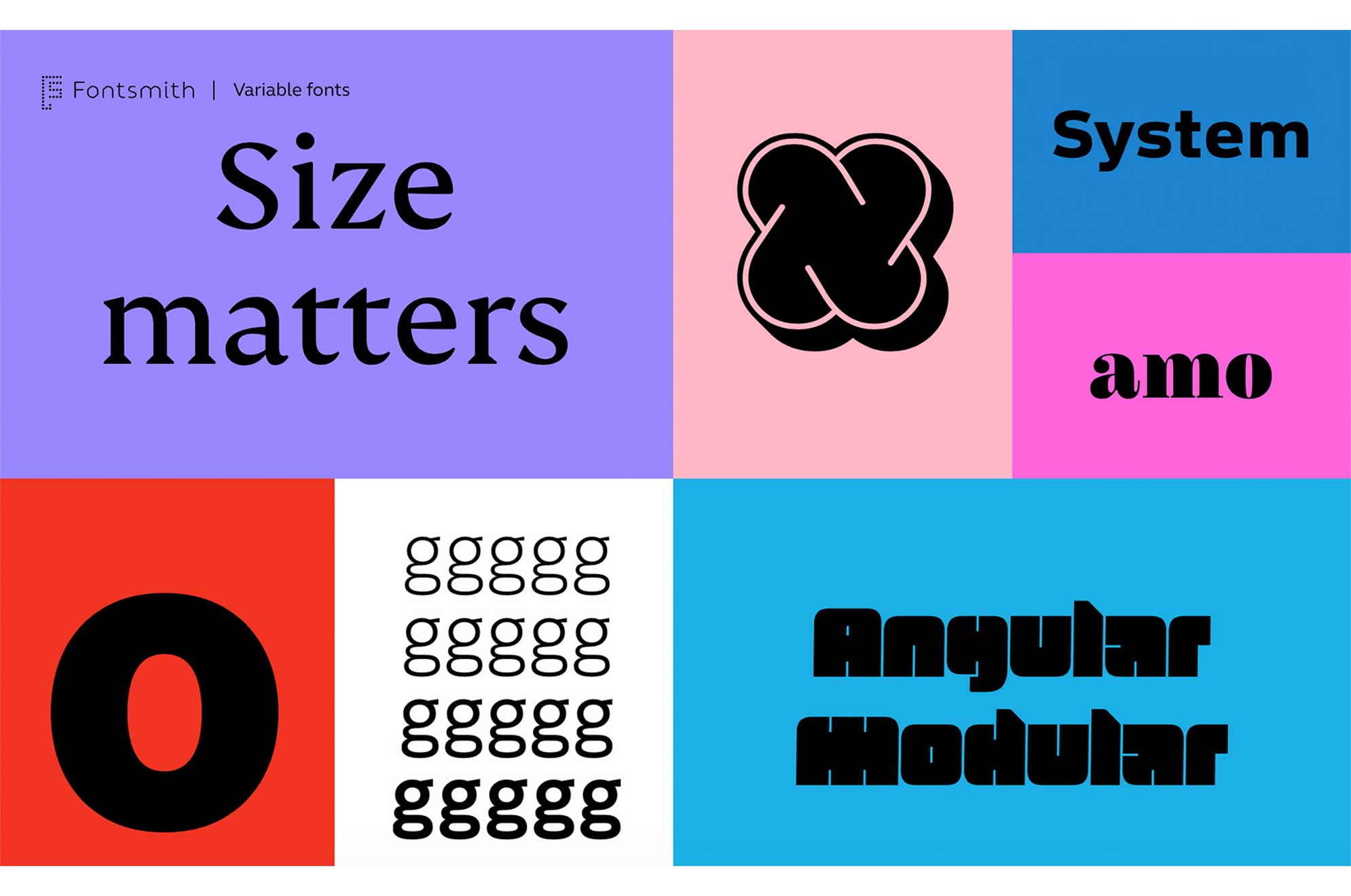
Obwohl die Technologie der variablen Fonts bereits vor rund drei Jahren im Markt eingeführt wurde, ist sie einer nicht ganz kleinen Anzahl Kreativer noch nicht vertraut: In der kürzlich erneut durchgeführten und inzwischen recht bekannten Umfrage von Mary Catherine Pflug zu den Kaufgewohnheiten von Schriften (“Font Purchasing Habits Survey“) gab ein Drittel der dort befragten Designer an, dass ihnen die Vorteile der variablen Schriften nicht bekannt seien. Und 39 Prozent hatten keine Ahnung, was variable Schriften überhaupt sind. Eine ziemlich ernüchternde Statistik für uns Schriftgestalter, denn wir sind alle überzeugt und begeistert von den Möglichkeiten, die diese Technologie uns eröffnet.
Mit variablen Fonts ist (fast) alles möglich
Einer der Kernaspekte variabler Schriften ist ihre enorme Leistungsfähigkeit und die damit einhergehende Tatsache, dass Marken mit ihnen völlig neue Möglichkeiten für ihre visuelle Kommunikation erhalten. Und weil wir Designer glauben, dass Schrift der Eckpfeiler jedes Corporate Designs ist, betrachten wir das als eine sehr gute Nachricht. Denn die Technologie verleiht der Schrift mehr Kraft und Energie, um die Identität einer Marke zu vermitteln.
Ich bin überzeugt, dass mit variablen Schriften eine neue Ära im Schriftdesign beginnt, denn mit ihnen ist (fast) alles möglich. Etwa weil eine variable Schrift eine einzelne, optimierte Schriftdatei ist, die sich aber wie eine komplette Schriftfamilie verhält und damit eine breite Palette von Stilen bereitstellen kann. Wenn eine traditionelle Schriftfamilie beispielsweise die Strichstärken Thin, Light, Regular, Bold und Black anbietet, kann diese als variable Schrift nicht nur alle diese Gewichtungen in einer Datei enthalten, sondern auch zig Zwischen-Strichstärken – und das in feinen Abstufungen. Dabei bleibt die Dateigröße überraschend klein, denn eine Variable Font-Datei enthält nicht die Beschreibung aller Stilzustände, sondern lediglich die Regeln, wie ein gewünschter Zustand entstehen soll.
Einen spielerischen Einstig in die Variable-Font-Technologie bietet diese Demo-Site von FontSmith, eine Foundry, die Monotype Anfang 2020 übernommen hat. Dort lassen sich mehrere Schriftfamilien per Schieberegler und mit eigenen Texten ausprobieren.
Die Stärke der variablen Font-Technik zeigt sich vor allem bei Großfamilien, wie beispielsweise der Universität Next, die 7 Strichstärken (Hairline bis Black), 3 Breiten (Condensed, Normal, Extended) und die dazugehörigen Kursiven bietet, also aus 7×3+21 = 42 Fonts besteht
…alle 42 Schnitte der klassischen Univers Next sind nun in einer einzigen Datei untergebracht, die nur 948 KB groß ist. Doch damit nicht genug, denn …
… tatsächlich liefert die Variable Font-Datei fast 80.000 Varianten der Univers Next aus, denn die Strichstärken-Achse verfügt über 600 statt „nur“ 7 Stufen, die Breite bietet 65 Abstufungen (statt 3) und die Kursiven sind natürlich auch enthalten. Fazit: variable Fonts sind kompakt, leicht zu handhaben und können über 1000 mal mehr Schnitte enthalten, was die typografische Freiheit enorm beflügelt.
Variable Fonts bieten Marken ein flexibles typografisches Werkzeug
Die Erfahrung zeigt, dass Unternehmen und bekannte Marken neuen Technologien gegenüber sehr aufgeschlossen sind. Die Technologie der variablen Schriften gibt Marken ein flexibles typografisches Werkzeug für eine breite Palette von Medien an die Hand. Für einen TV-Sender oder Streaming-Dienst hieße das etwa, dass Untertitel automatisch auf die Hintergrundfarbe reagieren und sich Strichstärken entsprechend ändern, so dass die visuelle Konsistenz und Lesequalität hoch bleibt – egal was im Hintergrund passiert. Variable Schriftarten können so programmiert werden, dass die Typografie dynamisch gestaltet ist. Das verleiht ihnen eine völlig neue, aber nützliche Qualität im digitalen Textdesign, die bei (statischen) Drucksachen wenig Sinn gemacht hätte. Die Möglichkeiten sind unerschöpflich, denn variable Schriften sind adressierbar, d.h. sie können in Echtzeit während ihrer Verwendung kontrolliert werden. Sie reagieren etwa auf Live-Daten (z.B. Heatmaps), auf die Kamera- oder Leseentfernung, auf die Geschwindigkeit eines Fahrzeugs oder auf Gesten. Die Bandbreite reicht von der reinen Kompensation, die dem Leser eine konstante Lesbarkeit garantiert, bis hin zu eher exzentrischen Typografien, bei denen die Buchstaben deutlich auf Lautstärke, Intonation, Bässe, Höhen oder Beats reagieren.
Variable Fonts bieten Entwicklern und Designern dynamische Möglichkeiten
Gegenwärtig erleben wir die Geburt intelligenter, adaptiver Branding-Systeme, bei denen die Schrift an erster Stelle steht und damit praktisch die Hauptrolle spielt. Jetzt ist also der genau richtige Zeitpunkt, sich mit variablen Schriften zu befassen und Antworten auf ein paar wichtige Fragen zu entwickeln: Wie schnell schneiden variable Schriften auf Webseiten ab? Wie weit können die Achsen einer variablen Schriftgestaltung gehen, bis sich das Erscheinungsbild von der visuellen Identität der Marke abhebt? Steigern variable Schriften die Markentreue oder gefährden sie die Corporate Identity? Sollten sehr bekannte Marken ein Schriftenexperiment wagen, oder besser nicht?
Entwickler und Designer zögern noch immer, variable Fonts anzuwenden. Aber langsam macht sich ein Wandel bemerkbar: Immer neue Ideen für Projekte entstehen, die dynamisch denken und sich von den Beschränkungen statischer Schriften lösen wollen. Die Nachfrage nach reaktionsschnellen, anpassungsfähigen Schriften wächst und konkrete Fragen zu variablen Fonts erreichen die Kreativszene. Das ist eine gute Nachricht, denn mit dem Einsatz variabler Schriften erleben visuelle Markenerlebnisse eine neue Ebene: Durch Kreativität und eine bisher unerreichte Funktionalität der Buchstaben.
Phil Garnham ist Creative Type Director und Schriftdesigner mit langjähriger Erfahrung in Design und Technik von Schriften für globale Marken. Bevor er zu Monotype kam, leitete er Schriftgestaltungsprojekte bei Fontsmith.
Das Gesicht des Monotype Studio-Schriftentwerfers Friedrich Althausen, der einen Font gebaut hat und verschenkt (über Github). Der Font hat die Achsen: Gesichtsmasketragen (macht abstehende Ohren), geschlossene Friseure (macht langes Haar und Bart) und Home-Schooling (macht müde Augen).